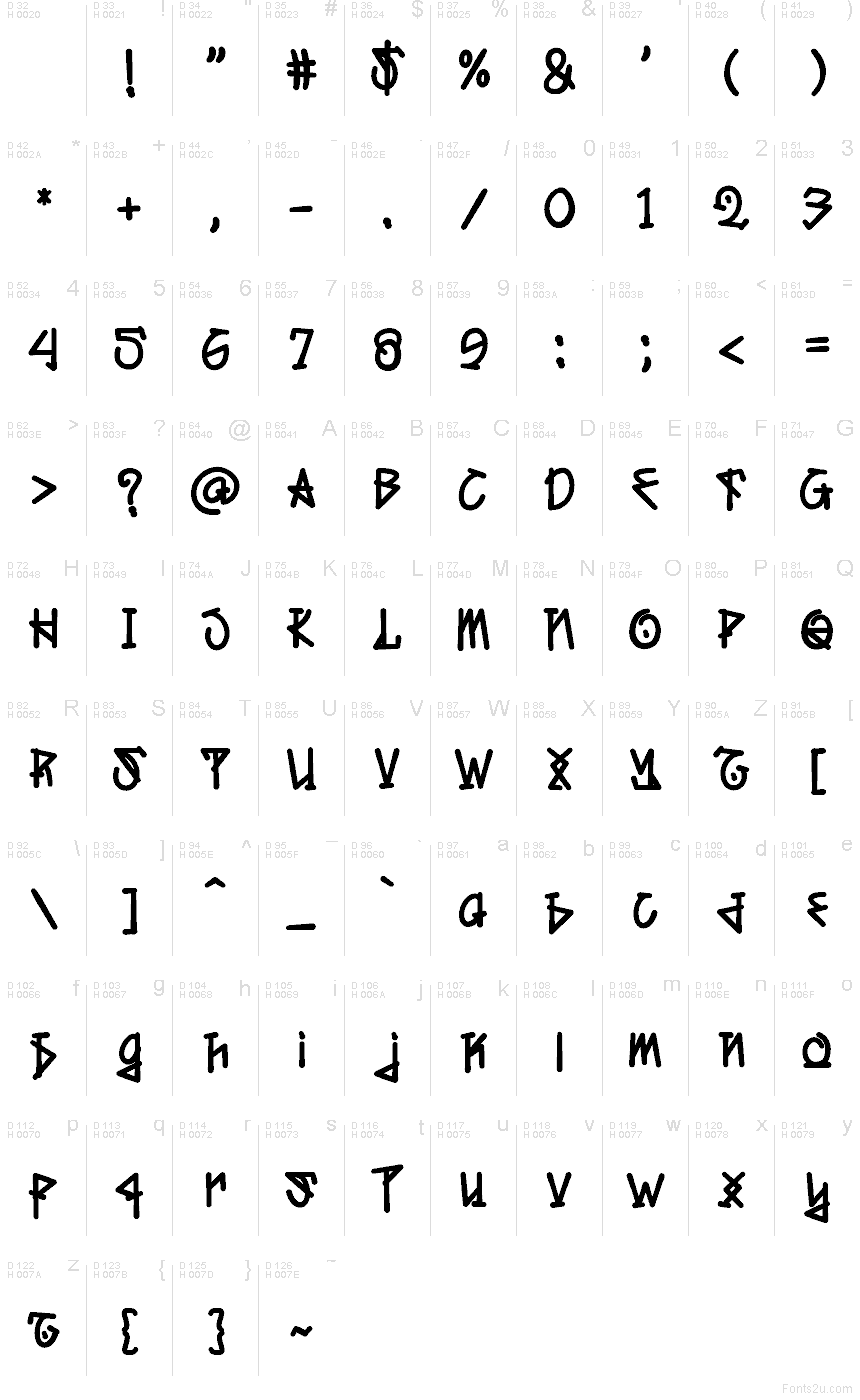
Waxioze
Waxioze, créée par Yumnacreative, est une police graffiti gratuite aux formes arrondies et dessinées à la main. Ses courbes douces et irrégulières confèrent à chaque lettre un aspect « tag » authentique, comme s'il venait d'être peint à la bombe. Avec ses formes simples, ses boucles compactes et ses traits transversaux ludiques, agrémentés de quelques gouttes et incisions, cette police conserve un caractère brut et spontané.
Waxioze est idéale pour les titres d'affiches, les autocollants, les designs de skate, le branding mural et les visuels pour réseaux sociaux, car elle capture toute l'énergie urbaine sans jamais sacrifier la lisibilité. Cette police gratuite convient également parfaitement aux couvertures, aux flyers d'événements et aux logos audacieux lorsque vous recherchez un lettrage au rendu rapide et aux contours irréguliers.